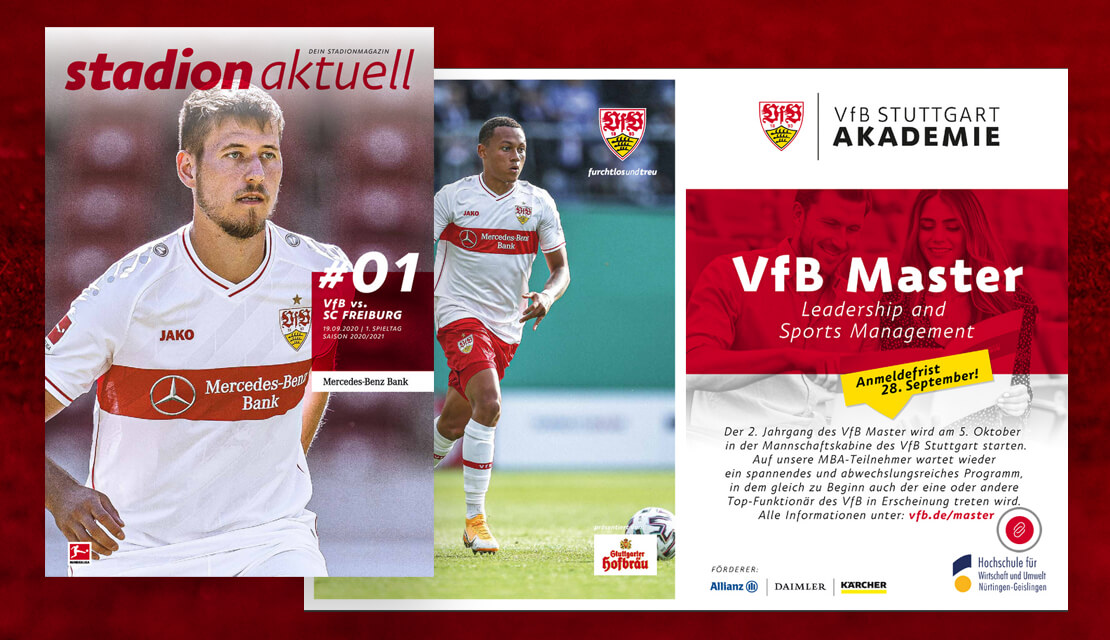
Die Schriften der Bundesliga-Vereine
Welche Schriften verwenden die Bundesliga-Vereine für ihr Corporate Design? Über die typografischen Vereins-Identitäten von Bayern München, Borussia Dortmund, Schalke und Co.
Branding und Design spielt auch im Sport eine immer wichtiger werdende Rolle. Die Vereins-Identität bestimmt maßgeblich das Image. Bundesliga-Clubs werden zu Marken und diese benötigen für das Corporate Design eine passende, typografische Grundlage. Auf welche Schriften die Vereine der Bundesliga setzen und ob es dabei Gemeinsamtkeiten oder Trends gibt, erfährt man hier. Wir werfen einen Blick auf Mitgliedermagazine, Stadionzeitschriften und weitere Medien aus der Fußball- und Vereinswelt.
Schriftart der Bundesliga
Den Anfang macht jedoch die Bundesliga selbst. Die verwendete Schrift nennt sich schlicht und einfach DFL. Sie wurde 2017 von Rosetta Type im Auftrag von Mutabor Design entwickelt. Die Fonts kommt in nahezu allen Bereichen der DFL Deutsche Fußball Liga zum Einsatz.
Bayern München Schriftart
Der FC Bayern München präsentiert sich mit der Hausschrift FC Bayern Sans. Gestaltet wurden die Fonts von TypeMates in Zusammenarbeit mit Interbrand Köln. Die Schriftart umfasst zur Zeit sieben Schnitte von »Light« bis »Bold« sowie entsprechende Versionen in »Condensed«. Eine zusätzliche Outline-Schrift wurde ebenfalls entwickelt.
Borussia Dortmund Schriftart
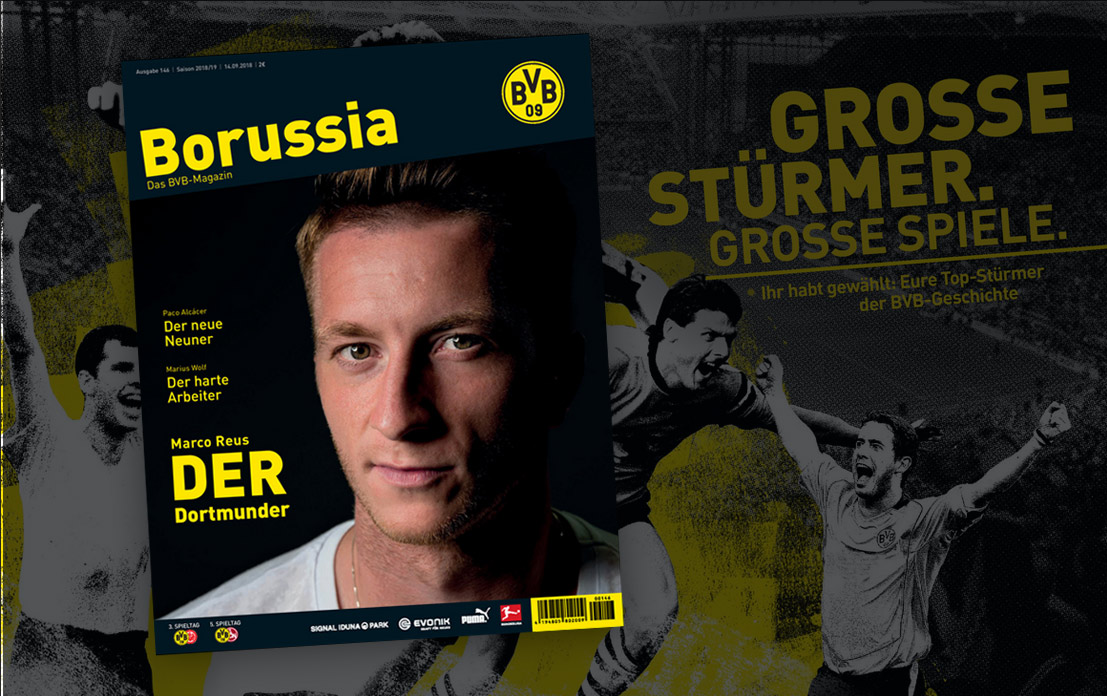
„Echte Liebe“ hat Borussia Dortmund nicht nur als Slogan gewählt, sondern auch zur Schriftart DIN* entwickelt. Die Schriftfamilie kommt vereinsmäßig in allen Bereichen der Borussen zum Einsatz. Der BVB nutzt primär die Schnitte Light, Regular, Bold und Black.
Schriftart von Borussia Mönchengladbach
Die Fohlen haben sich 2018 von der Kommunikations-Agentur L&L einen neuen Markenauftritt verpassen lassen. Im Zuge dessen wurde auch eine neue Schriftart eingeführt. Borussia Mönchengladbach setzt plakativ in Grün und Schwarz den Font Bungee ein. »FohlenEcho«, das Magazin der Borussen, macht von dem Font in der Regular-Version Gebrauch. Die Schrift ist von David Jonathan Ross gestaltet und kostenlos bei Google Fonts als Download verfügbar.
Schalke 04 Schrift
Der FC Gelsenkirchen-Schalke 04 e.V. setzt für seine Hausschrift in der Saison 2020/2021 auf Schnitte der Schriftfamilie Corporate S, die unter anderem auch als »Mercedes-Schriftart« bekannt ist. Sowohl der Schalker Kreisel als auch die Knappenschmiede verwenden die Schnitte der Corporate. Entworfen hat die Fonts seinerzeit Prof. Kurt Weidemann.
RB Leipzig Fonts
Der RasenBallsport Leipzig e.V. nutzt Bull als Hausschrift. 2016 wurde das Corporate Design von Red Bull redesigned. Die TypeMates aus Hamburg steuerten für Red Bull TV die entsprechende Schriftfamilie bei.
Im Web zeigt man sich außerdem plakativ mit der Grand von Monotype. Das KLUB-Magazin der roten Bullen verwendet zudem Schnitte der Futura*.
TSG Hoffenheim Schriftarten
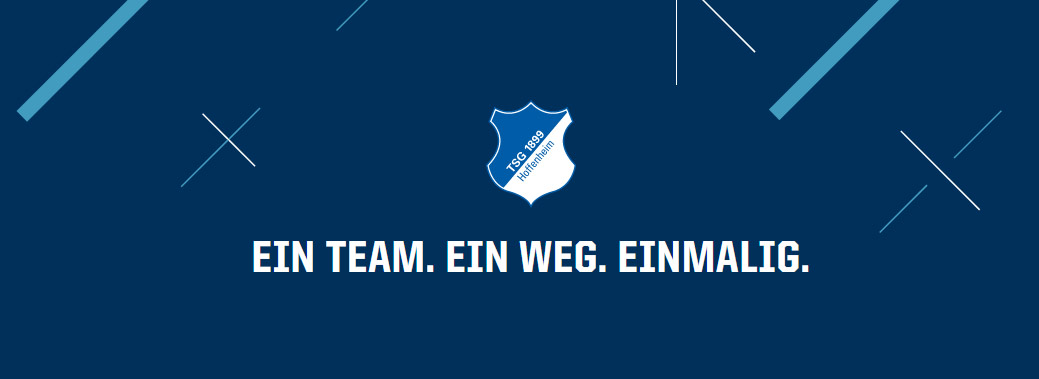
Die TSG Hoffenheim setzt für ihre Printmedien und im Web auf die Schriftart United von HouseIndustries. Die Schriftfamilie gibt es in vielen Varianten. Für Überschriften kommt anscheinend häufig die SemiCondensed Black zum Einsatz. Bei Fließtexten sind man die National aus der Schriftenschmiede Klim Type Foundry.
Bayer 04 Leverkusen Font
Die Werkself bekam um 2016 herum ein neues Facelift von stay golden verpasst. Im Rahmen des Corporate Designs wurde nicht nur das Logo neu angepasst, sondern auch eine neue Schrift für den Bundesliga-Verein eingeführt. Der Font nennt sich FB Heron Sans und wurde dem Kürzel nach von Font Bureau entwickelt. Die Schriftfamilie kann man derzeit anscheinend nicht mehr käuflich erwerben.
Eintracht Frankfurt Schriftarten
Im markanten Corporate Design präsentiert sich der Bundesliga-Verein Eintracht Frankfurt. Der 2017 vom Rat für Formgebung mit dem German Brand Award in Gold ausgezeichnete Auftritt verwendet offensichtlich die Schriftfamilie Univers* in diversen Schnitten – von Ultra Condensed bis Extra Black Oblique – und sorgt somit für ein modernes Erscheinungsbild.
Mainz 05 Schriften
Gemeinsam mit dem Agenturduo aus ONE8Y und Done by people hat der Bundesligaclub 1. FSV Mainz 05 eine eigene Typografie entwickelt. Zentrales Element bildet das »M« des Vereinslogos.
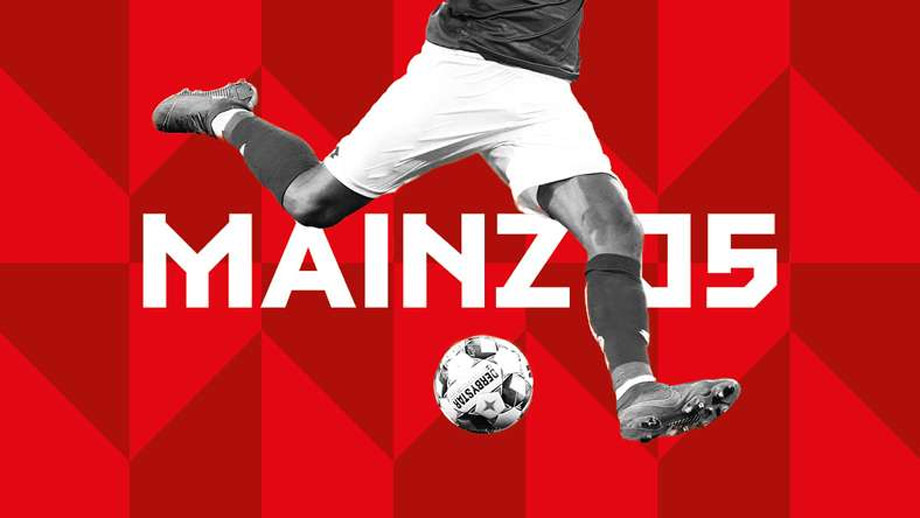
Das abgeleitete Gestaltungskonzept zieht sich vom Layout digitaler Medien bis hin zu Plakaten, Fahnen und mehr. Die Schriftarten nennen sich M05 Headline bzw. M05 Text und sind über Schriftenshops nicht erhältlich.